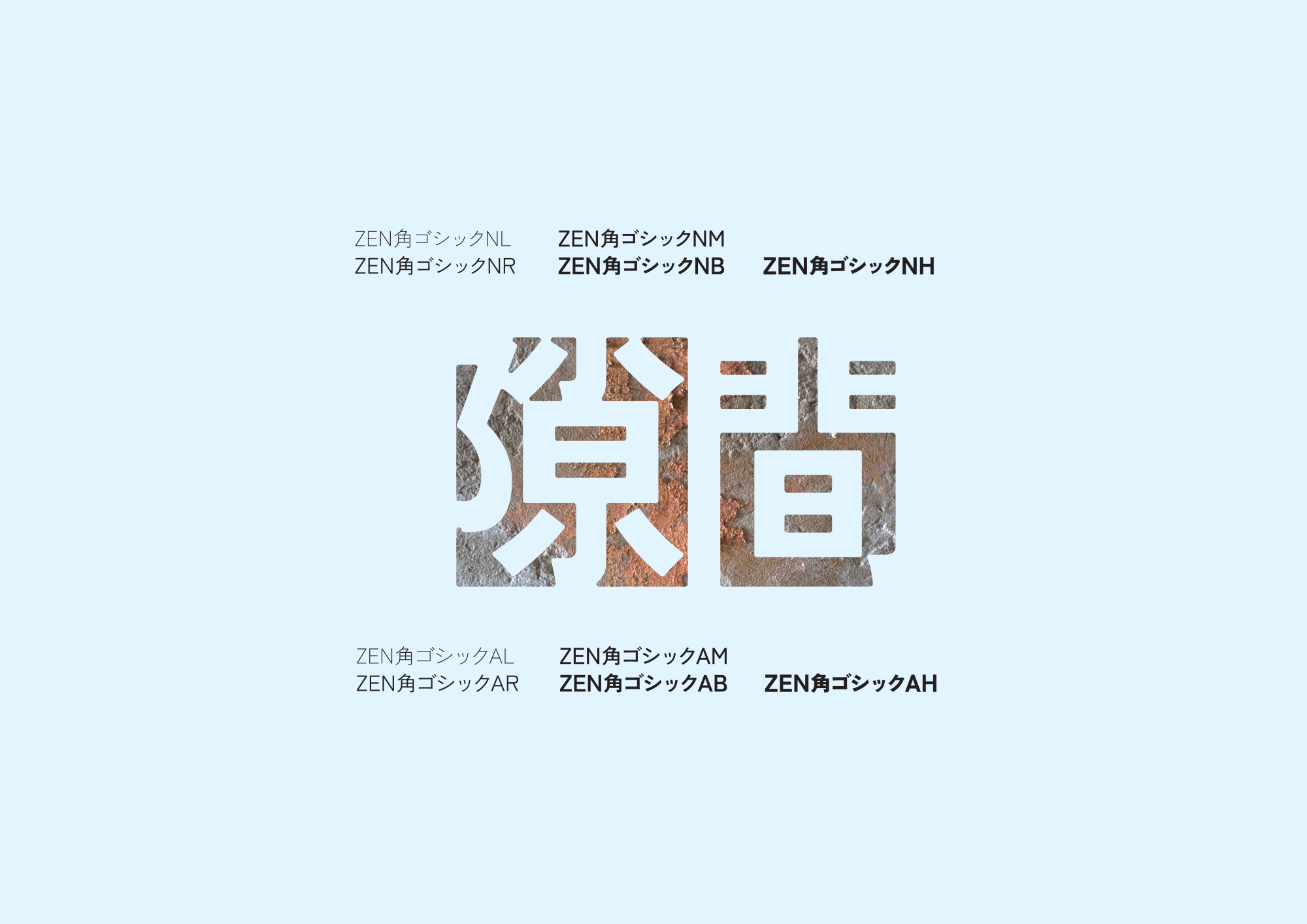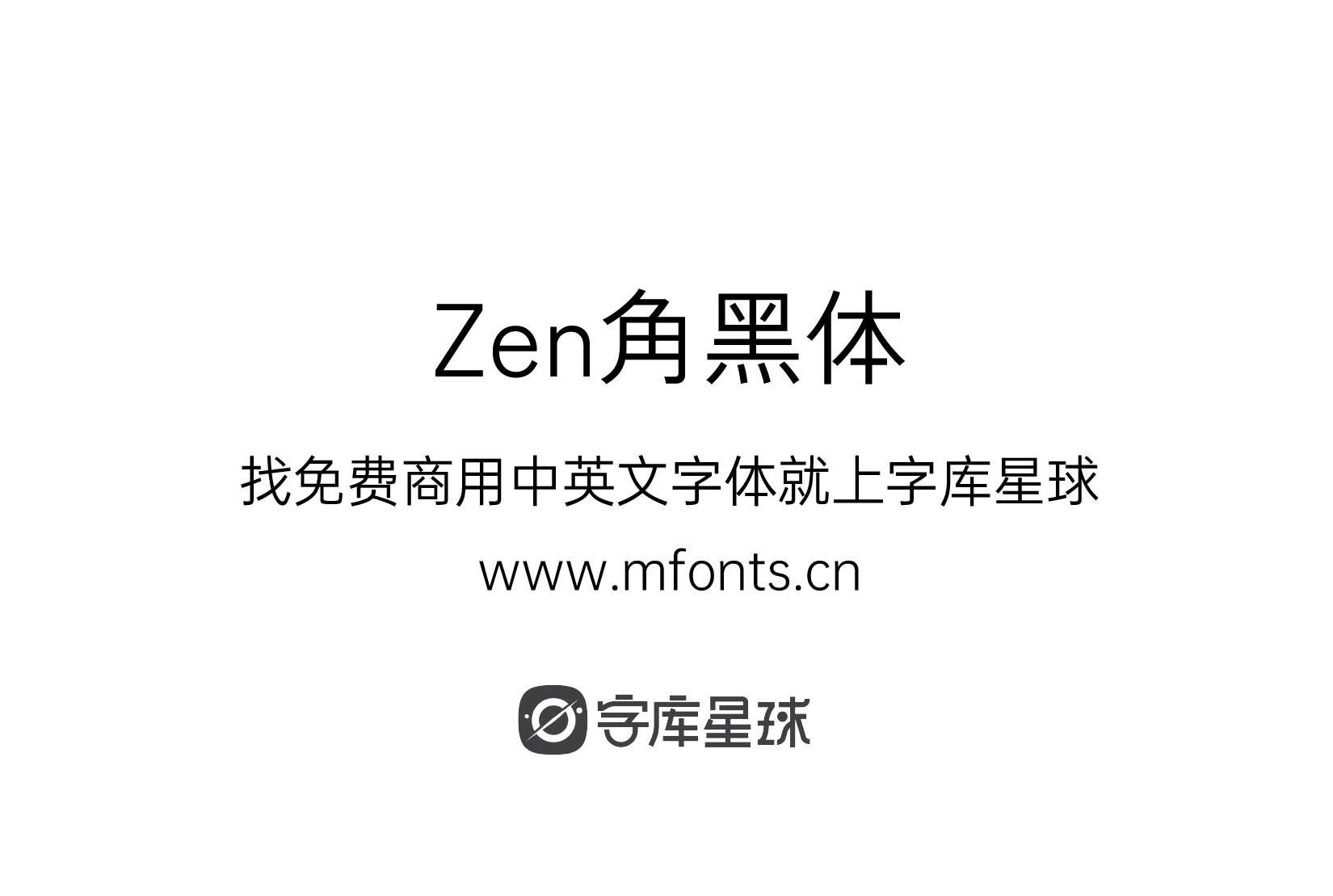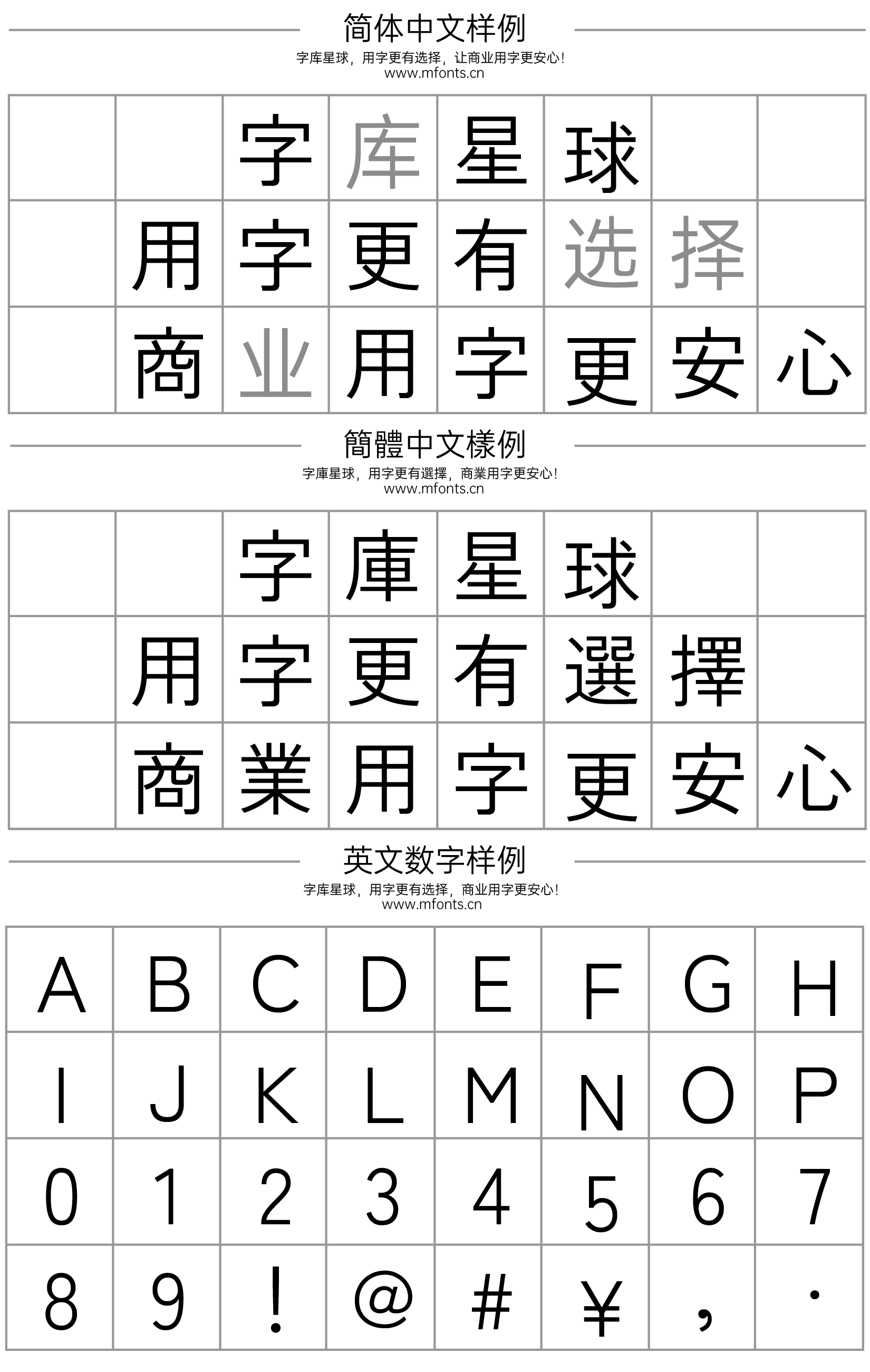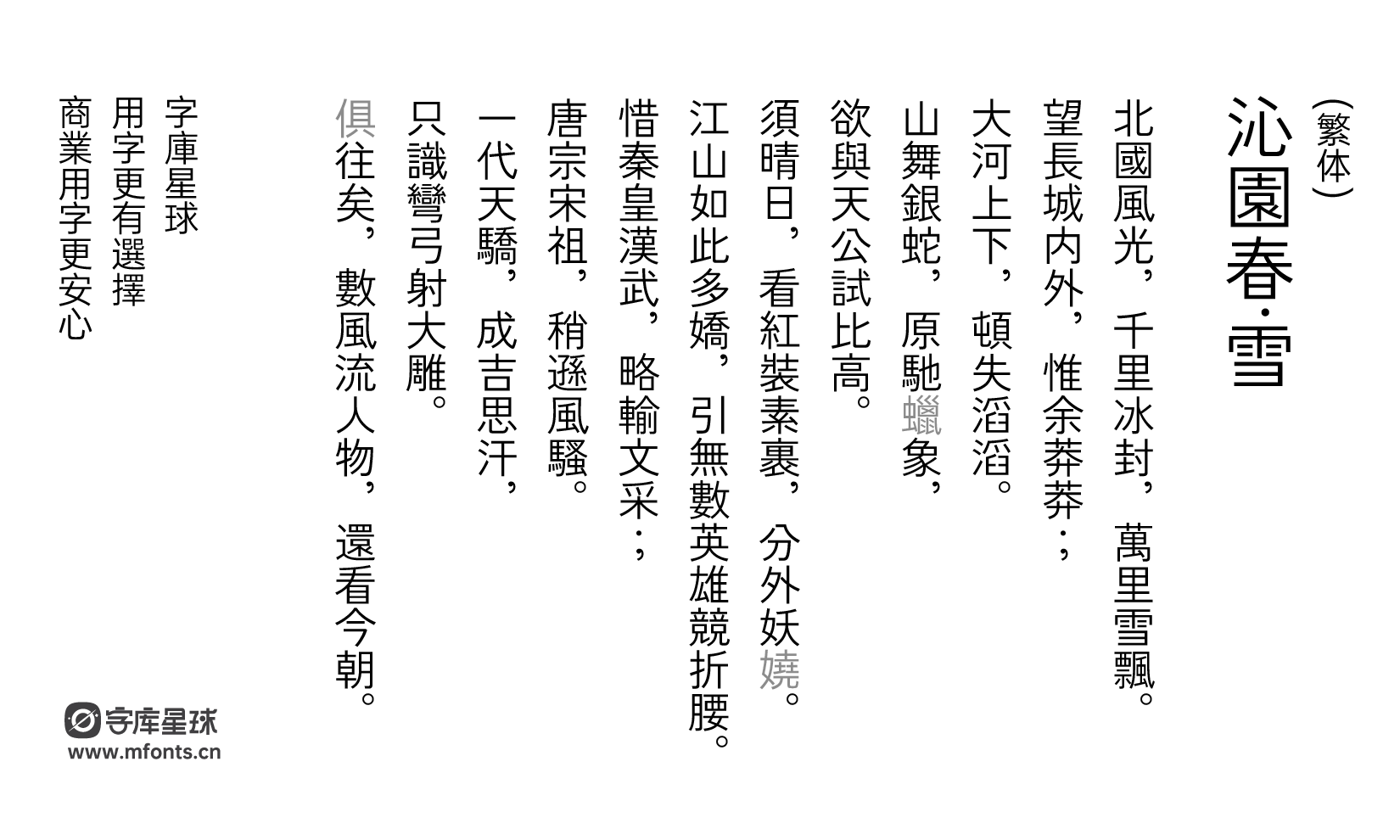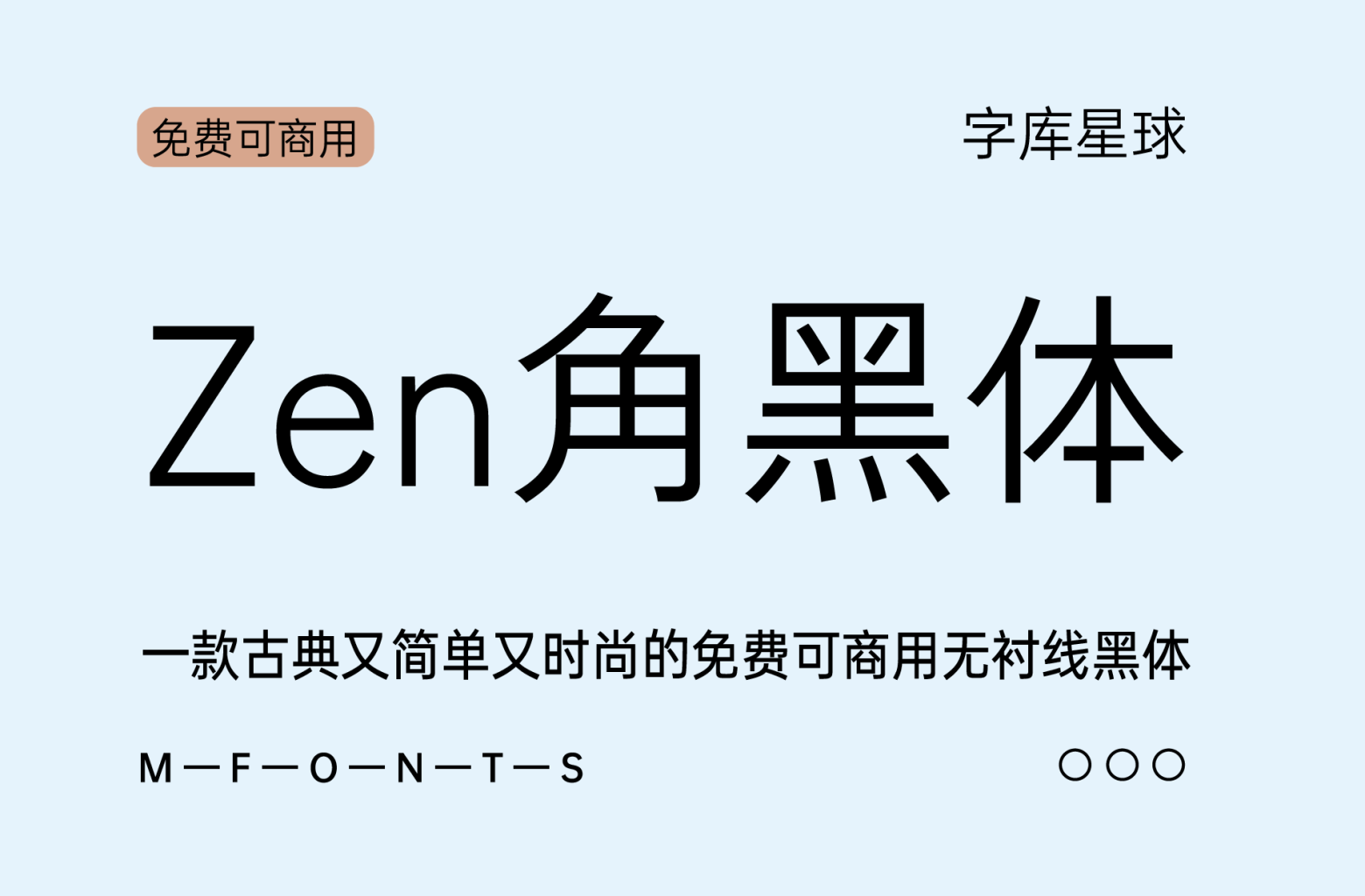
Zen角黑体
Zen 角黑体N 是一个基本的日本 san serif(哥特式)家族。 使用此字体,无需任何专业的详细安排,即可表达精细的排版。 由于独特而简单的设计,它自然具有很高的易读性。 易于使用和阅读。
Zen 角黑体A 是一个古典又简单又时尚的无衬线字体家族。 由于正统的字体设计,清晰易读。 非常适合各种用途,从标题到文本,甚至标题。